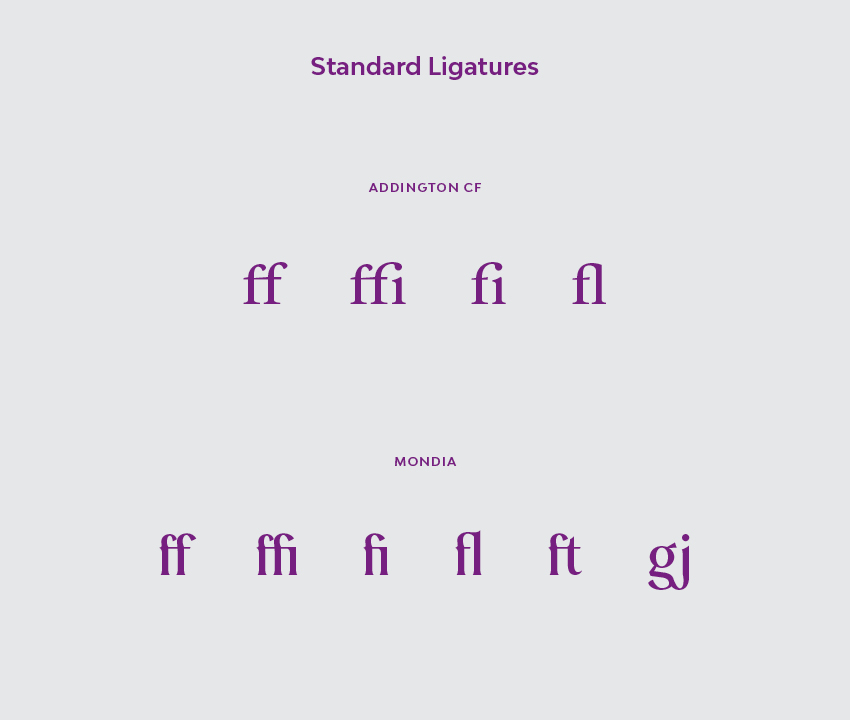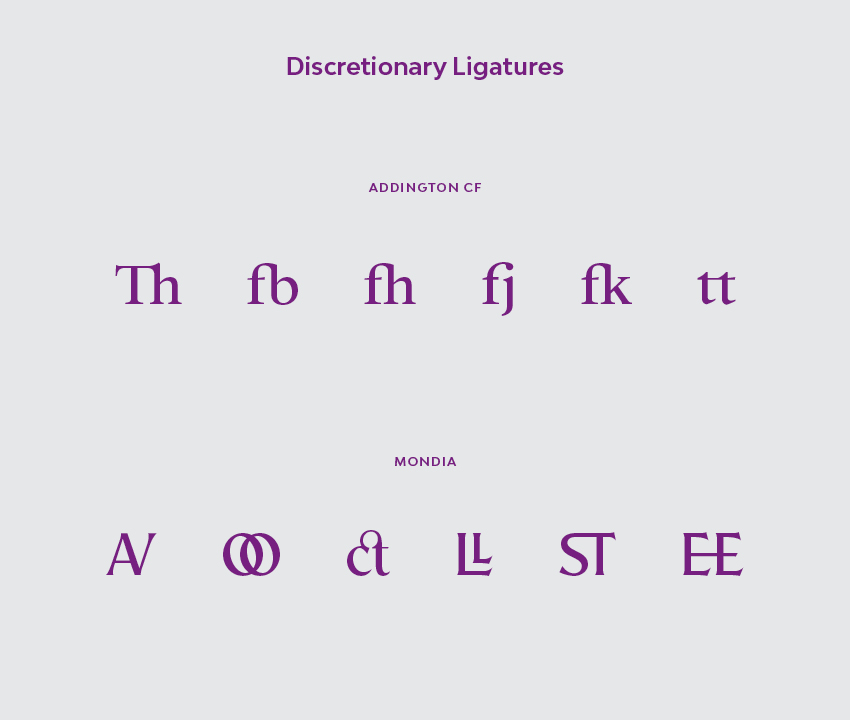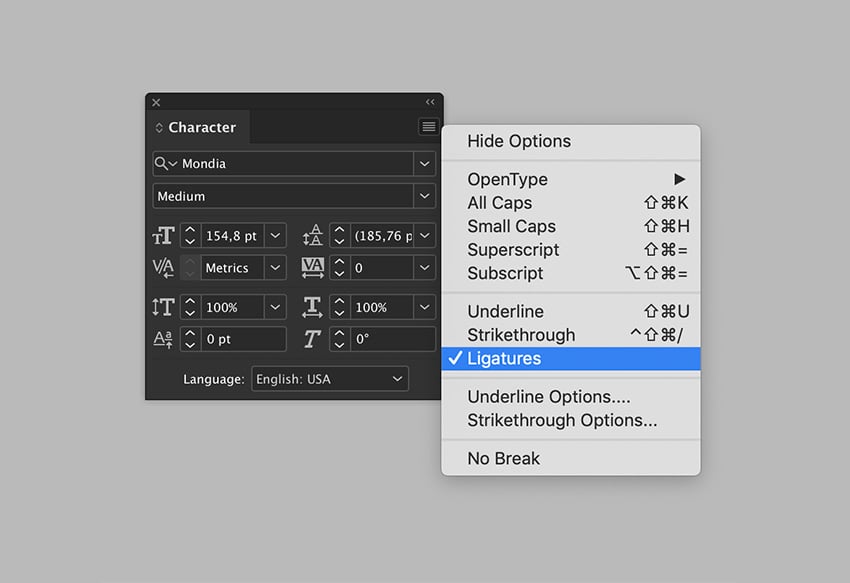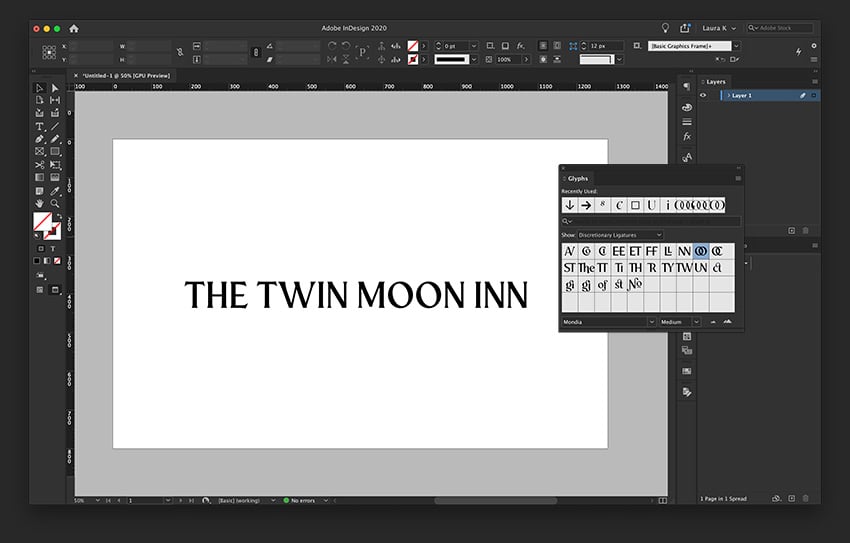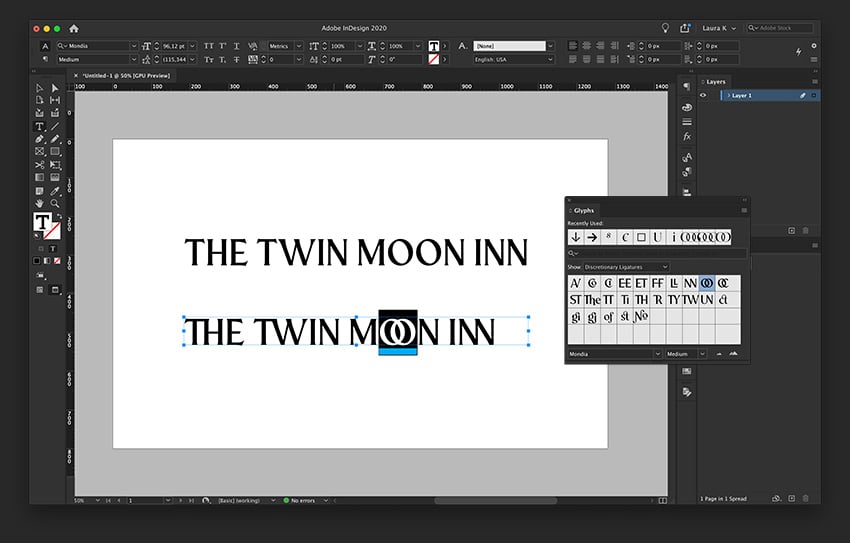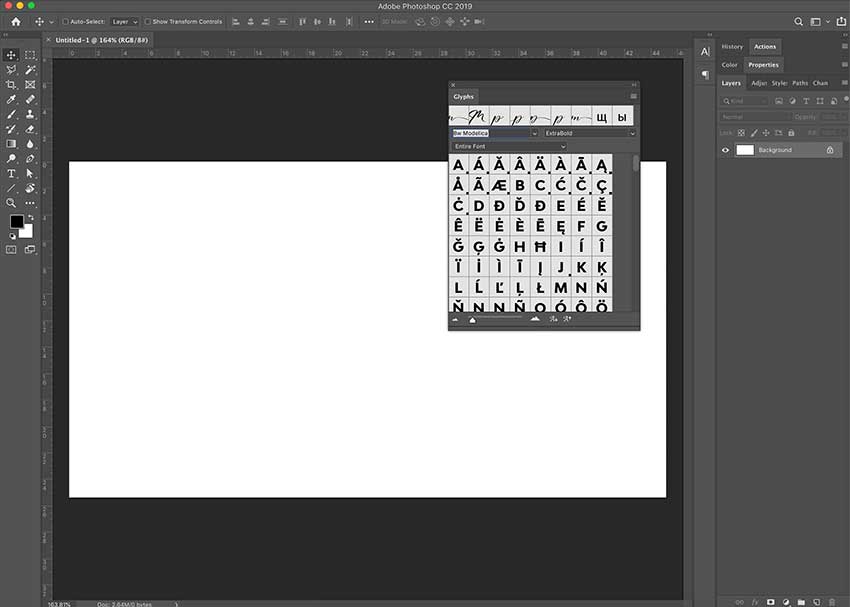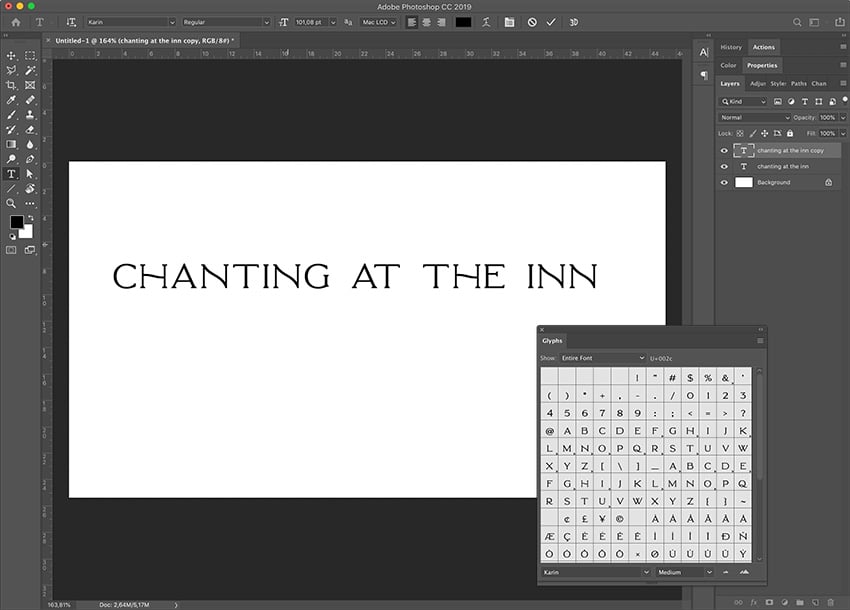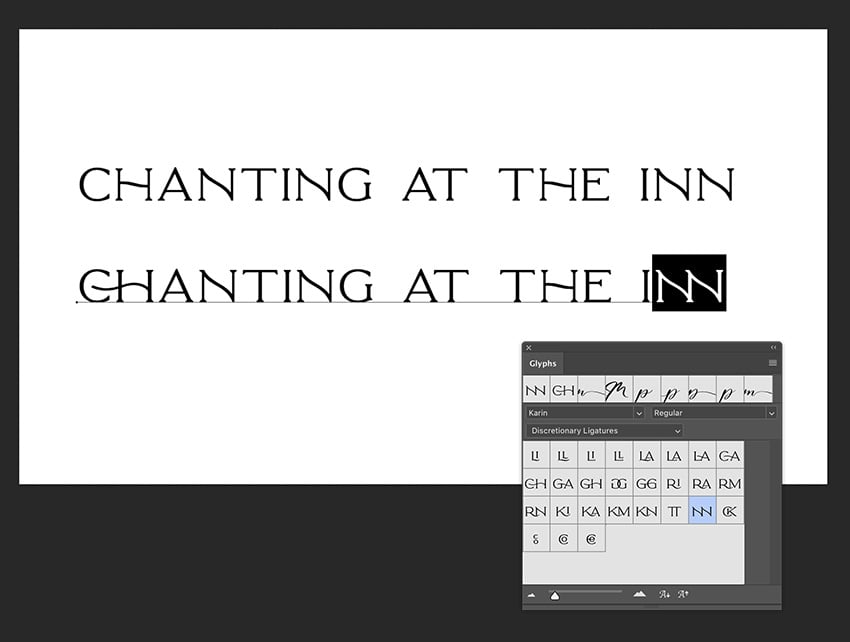
در این آموزش نگاهی میاندازیم به اینکه لیگچرهای فونت چیست و چگونه از آنها استفاده کنیم و برخی از بهترین فونتهای لیگچر را معرفی میکنیم.
لیگچرهای فونت یکی از هدفمندترین عناصر در طراحی گرافیکی به خصوص در فرمهای طولانی متن هستند.
کلمه لیگچر از کلمه لاتین ligare به معنای «گره یا پیوند» گرفته شده است. یک لیگچر در فونتها دو یا سه کاراکتر را در یک کاراکتر واحد ترکیب میکند تا به کرنینگ و برای اهداف تزئینی کمک کند.
برای این آموزش، از دو فونت موجود در فروشگاه استفاده میکنیم. Karin دارای لیگچرهای فونت بسیار خوبی است که میتوانیم از آنها برای نشان دادن نحوه استفاده از لیگچرها در فتوشاپ یا هر نرمافزار دیگر ادوبی استفاده کنیم. ما همچنین از Mondia استفاده میکنیم تا بتوانید لیگچرهای رایج موجود در اکثر فونتها را بررسی کنید.
یک لیگچر استاندارد در فونتها، دو یا سه کاراکتر را در یک کاراکتر ترکیب میکند. هنگامی که برخی از کاراکترها فضای افقی کاراکتر بعدی را اشغال میکنند، این نوع لیگچرها به هستهبندی یا کرنینگ کمک میکند. بسته به زبان، لیگچرهای مختلفی وجود دارد. در زبان انگلیسی، لیگچرهای با ff، ffi، fi و fl رایج است زیرا کلمات زیادی با این ترکیبها وجود دارد. لیگچرها باید با دقت استفاده شوند زیرا اگر متن شما دارای فاصله حروف گسترده باشد، میتوانند بیش از حد واضح به نظر برسند.
نوع دوم لیگچرها، لیگچرهای اختیاری هستند و اینها معمولاً تزئینی هستند. این لیگچرها همچنین دو یا سه کاراکتر را در یک طرح کاراکتر برازنده ترکیب میکنند. ترکیباتی مانند TH، th، ck، ct، et، و st مانند کاراکترهای دوگانه مانند oo، tt، و ll وجود دارد. درست مانند لیگچرهای استاندارد، این نوع لیگچرها نیز باید با دقت مورد استفاده قرار گیرند.
مهم است که روشن شود که هر فونتی حاوی لیگچرهای استاندارد و اختیاری نیست. هر فونت متفاوت است، و در نهایت تصمیم طراح فونت است که آنها را اضافه کند.
ادوبی ایندیزاین را باز کنید و یک سند جدید ایجاد کنید. برای باز کردن پنل گلیفها به Window > Type > Glyphs بروید.
برای فعال یا غیرفعال کردن لیگچرها، با رفتن به Window > Type > Character، پنل کاراکتر را باز کنید. روی منوی گوشه سمت راست بالا کلیک کنید و Ligatures را انتخاب کنید تا آنها را فعال یا غیرفعال کنید.
ابزار متن (T) را از نوار ابزار انتخاب کنید و هر متنی را تایپ کنید. برای این آموزش، من از "TWIN MOON INN" استفاده خواهم کرد. فونت را روی Mondia تنظیم کنید.
در Glyphs panel، سابسِت لیگچرها را روی Standard Ligatures تنظیم کنید.
برای استفاده از لیگچرها در پنل گلیفها، جفت نویسههایی را که میخواهید با استفاده از ابزار متن (T) تغییر دهید، انتخاب کنید. روی لیگچر مورد نظرتان در پنل گلیفها دوبار کلیک کنید. به یاد داشته باشید که اگر میخواهید به طور خودکار لیگچرها نشان داده شوند، آنها در کاراکتر پنل فعال کنید.
ادوبی فتوشاپ را باز کنید و یک سند جدید ایجاد کنید. برای باز کردن پنل گلیفها به Window > Glyphs بروید.
برای فعال یا غیرفعال کردن لیگچرهای خودکار، با رفتن به Window > Character، کاراکتر پنل را باز کنید. در این پنل، دکمه اول Standard Ligatures (لیگچرهای استاندارد) را فعال میکند، در حالی که دکمه سوم Discretionary Ligatures (لیگچرهای اختیاری) را فعال میکند. من هر دو را غیرفعال میکنم تا بتوانیم به پانل گلیفها نگاهی بیندازیم.
ابزار متن (T) را از نوار ابزار انتخاب کنید و هر متنی را که میخواهید تایپ کنید. برای این آموزش، من از "Chanting at the Inn" استفاده خواهم کرد. فونت را روی Karin تنظیم کنید.
در پنل Glyphs، سابسِت لیگچرها را روی Ligatures Discretionary تنظیم کنید تا به لیگچرهای موجود در فونت دسترسی داشته باشید. همه فونتها شامل لیگچرهای اختیاری و استاندارد نیستند، بنابراین بررسی هر دو مفید است.
برای استفاده از لیگچرها در پنل Glyphs، جفت نویسههایی را که میخواهید با استفاده از ابزار متن (T) تغییر دهید، انتخاب کنید. روی لیگچر مورد نظر خود در پانل گلیفهای دوبار کلیک کنید.
ادوبی ایلاستریتور را باز کنید و یک سند جدید ایجاد کنید. برای باز کردن پنل Glyphs به Window > Type > Glyphs بروید.
برای فعال یا غیرفعال کردن لیگچرها، با رفتن به Window > Type > OpenType، پنل OpenType را باز کنید. در این پانل، دکمه اول Standard Ligatures را فعال میکند، در حالی که دکمه سوم Discretionary Ligatures را فعال میکند. من هر دو را غیرفعال میکنم تا بتوانیم به پنل گلیفها نگاهی بیندازیم.
ابزار متن (T) را از نوار ابزار انتخاب کنید و هر متنی را تایپ کنید. برای این آموزش، من از "finding waffles" استفاده خواهم کرد. فونت را روی Mondia تنظیم کنید.
موندیا حاوی لیگچرهای اختیاری و استاندارد است. در پنل Glyphs، سابسِت گلیفها را روی Standard Ligatures تنظیم کنید.
برای استفاده از لیگچرها در پنل Glyphs، جفت نویسههایی را که میخواهید با استفاده از ابزار متن (T) تغییر دهید، انتخاب کنید. روی لیگچر مورد نظرتان در پنل گلیفها دوبار کلیک کنید. به یاد داشته باشید که اگر میخواهید به طور خودکار لیگچرها نشان داده شوند آنها را در پنل OpenType فعال کنید.
اکنون که میدانید چگونه لیگچرها را در ایندیزاین و نرمافزارهای دیگر روشن کنید، وقت آن است که از آن لذت ببرید! بیایید نگاهی به برخی از فونتهای فوقالعاده بیندازیم که حاوی جالبترین لیگچرهای فونت هستند.
این فونت اسکریپت شیک بسیار خوش ساخت است. دارای حروف کوچک شروع و پایان است و همچنین اسواشهایی که میتواند یک فونت نمایشی عالی ایجاد کند. شما همچنین یک کتابخانه لیگچری گسترده با ترکیبی از کاراکترهای متعدد برای ایجاد فونت تا حد امکان واقعی دریافت میکنید.
اسکریپت هازارد یک فونت الهام گرفته از رترو است که با حروف دستی ترکیب شده است. منحنیهای روی هر کاراکتر صاف و بسیار خوش ساخت و کامل هستند. این فونت کِرسیو شامل اسواشهای بونوس است که برای لوگوها و برندسازی مناسب است. لیگچرها میتوانند به شما کمک کنند تا از ترکیبات منحصر به فرد دو کاراکتری استفاده کنید و ظاهری بسیار خاص به لوگوی شما میبخشد.
این فونت سریف نرم مدرن و پررنگ است. حال و هوای رمانتیک دارد و بسته شامل مجموعه کاراکترهای اسواش و لیگچرهای عالی است. از آن برای برندینگ یا تیتر و عنوان استفاده کنید و با ترکیب کاراکترها ظاهری منحصر به فرد ایجاد کنید.
در این مقاله به شما نشان دادیم که لیگچر چیست، نحوه استفاده از لیگچرها در ایلاستریتور، فتوشاپ و ایندیزاین و نحوه روشن و خاموش کردن لیچگرها در ایندیزاین. لیگچرها در ایندیزاین برای اهداف استایلیستیک و صرفهجویی در فضا با کرنینگ مفید هستند.